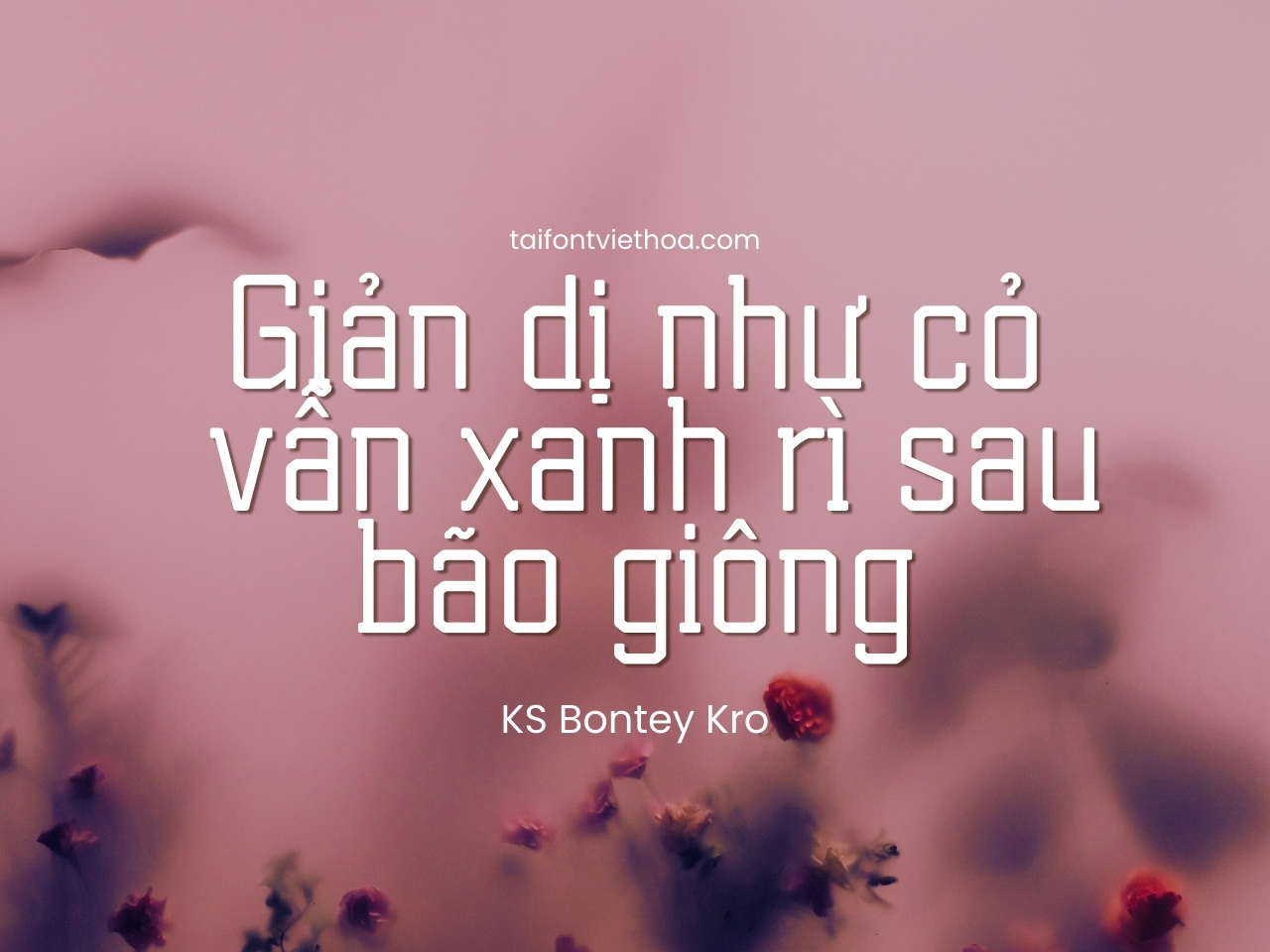
Font việt hóa Ks Bontey Kro Font Tiếng Việt
Giới thiệu về font Ks Bontey Kro và phiên bản Việt hóa
Ks Bontey Kro là một phông chữ sans-serif hiện đại do nhà thiết kế Kiên Sinh phát triển, được lấy cảm hứng từ cấu trúc chữ đơn giản, góc cạnh rõ nét thường thấy trong các hệ thống bảng điện tử và giao diện kỹ thuật số. Với ý tưởng kết hợp giữa yếu tố công nghệ và kiểu chữ hiện đại, font tạo nên một diện mạo thị giác sắc sảo, phù hợp cho truyền thông số và in ấn kỹ thuật cao.
Phiên bản Việt hóa được chính Kiên Sinh thực hiện, đảm bảo tương thích hoàn toàn với tiếng Việt có dấu và các ký tự đặc trưng Unicode. Bên cạnh hỗ trợ đầy đủ tiếng Việt, Ks Bontey Kro còn tương thích với hơn 80 ngôn ngữ sử dụng bảng chữ cái Latin, tạo điều kiện triển khai trong nhiều dự án quốc tế. Font này được taifontviethoa.com chọn lọc, kiểm duyệt và chia sẻ, như một phần trong nỗ lực cung cấp kho font Việt hóa chất lượng cho cộng đồng thiết kế, đặc biệt trong các lĩnh vực giáo dục, công nghệ và truyền thông sáng tạo.
Kiểu dáng sans-serif tối giản và khả năng ứng dụng linh hoạt
Ks Bontey Kro sở hữu cấu trúc sans-serif rõ ràng, thân chữ gọn gàng, chiều cao đồng đều, giúp font có khả năng trình bày tốt ở nhiều kích thước khác nhau. Với các nét thẳng và bo nhẹ ở đầu chữ, font mang lại cảm giác thân thiện nhưng vẫn giữ được vẻ chuyên nghiệp. Thiết kế này rất lý tưởng cho tiêu đề website, giao diện app, bảng biểu, banner sự kiện hay hệ thống nhận diện thương hiệu trong lĩnh vực kỹ thuật số.
Font đặc biệt phù hợp với các ngành như công nghệ thông tin, giáo dục trực tuyến, thiết kế kỹ thuật, hội chợ công nghệ, dự án truyền thông số, cũng như các sản phẩm quảng cáo có định hướng trẻ trung, hiện đại. Đây là sự lựa chọn hiệu quả để thể hiện thông tin rõ ràng, thu hút sự chú ý mà không làm mất đi tính chuyên nghiệp của dự án.